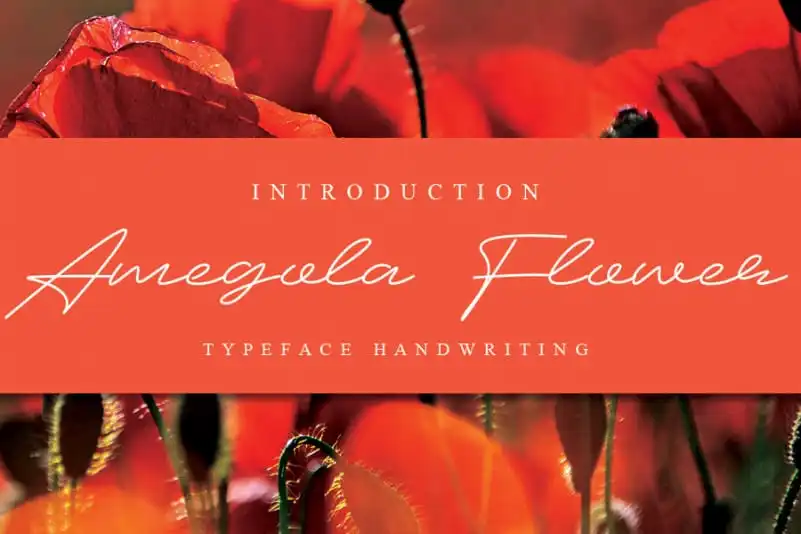
Amegola Flower Handwritten Font – Fonte Grátis
Amegola Flower Handwritten Font
A Amegola Flower Handwritten Font é uma elegante e relaxada fonte escrita à mão cívilizadamente que se destaca pela sua simplicidade e frescura. Uma das características mais apreciadas desta fonte é o seu charme timeless, tornando-a perfeita para qualquer conceito de design. Seja você criando um layout para a web ou desenvolvendo um material gráfico impresso, essa fonte será uma escolha conveniente e imediatamente reconhecível. Ideal tanto para textos menores quanto para grandes títulos, Amegola é a escolha perfeita se buscas um toque floral na tua próxima criação visual. Seja você um designer de interfaces, ilustrador ou criador de conteúdo digital, este fonte oferece uma maneira única e sofisticada de adicionar personalidade aos teus trabalhos.